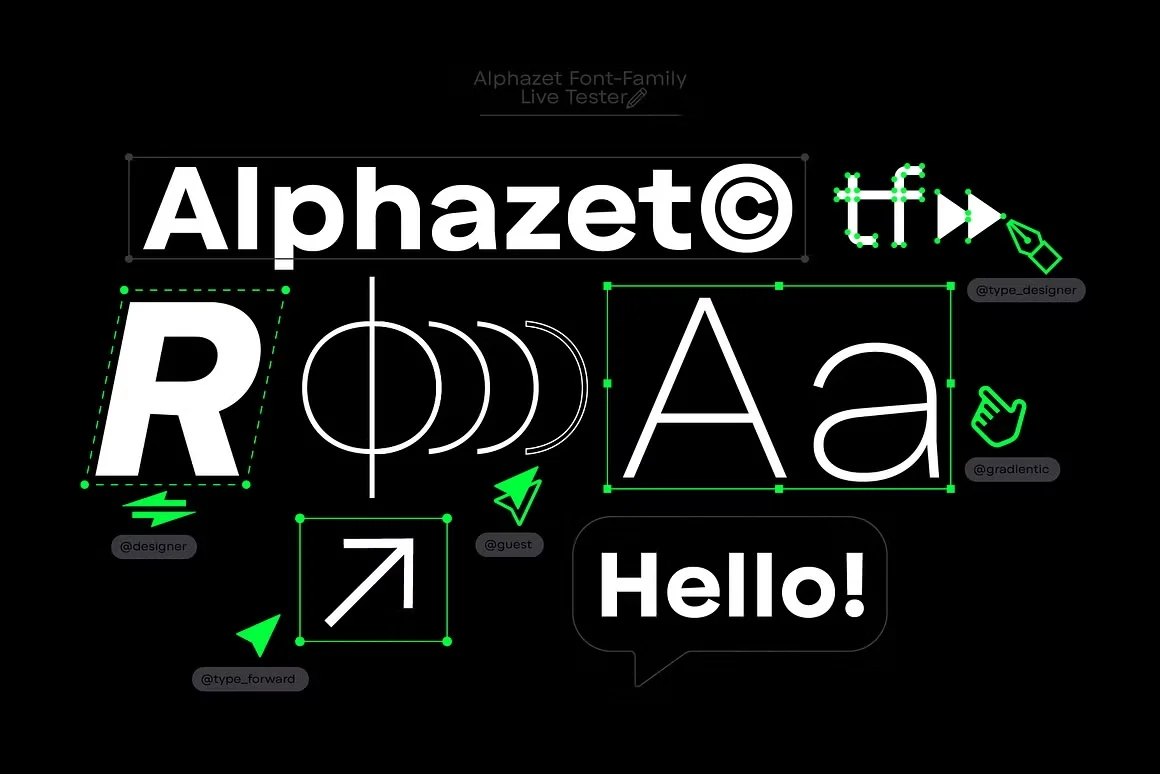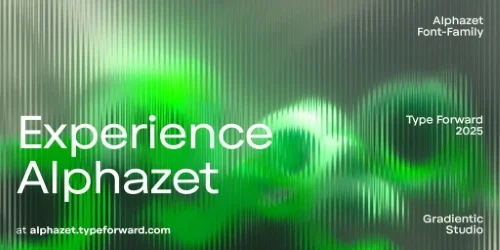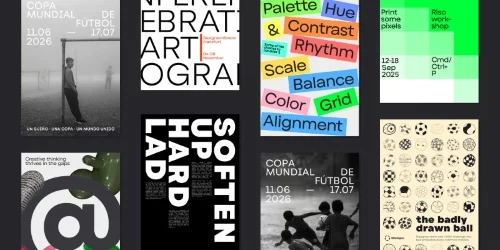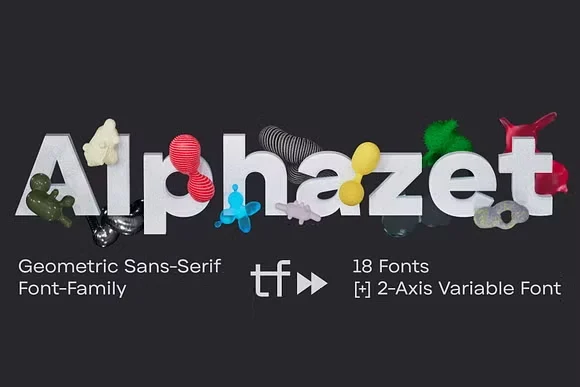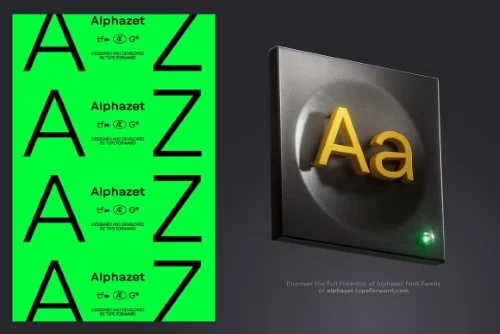
فونت هندسی مدرن Alphazet Variable Font Family
ساختار هندسی بینقص، ۱۸ استایل استاتیک + فونت وریبل ۲ محوره برای برندینگ و وب
استفاده از فونت هندسی Alphazet که با همکاری طراح برجسته Luboslav Boyanov توسعه یافته، حسی از استحکام، قدرت و مدرنیته به دیزاینهای شما میبخشد. این تایپفیس بر پایه اشکال خالص هندسی طراحی شده و با داشتن کنتراست کم در خطوط و x-height بلند، بالاترین میزان خوانایی را در متون طولانی و جذابیت فوقالعادهای در تیترها و پوسترهای بزرگ ایجاد میکند.
این مجموعه شامل ۱۸ استایل استاتیک مجزا (۹ وزن کامل از Thin تا Black به همراه نسخههای Oblique) و همچنین یک فایل کامل وریبل فونت (Variable Font) با ۲ محور تنظیم است که کنترل ۱۰۰٪ وزن و زاویه فونت را در پروژه به شما میدهد.
Ligatures, Stylistic Sets, Fractions
بیش از ۲۲۰ زبان (لاتین، سیریلیک و یونانی)
ویژگیهای شاهکار فونت هندسی Alphazet
تکنولوژی هوشمند وریبل فونت (2 Axes Variable Font)
وجود فایل وریبل فونت دو محوره به طراحان و توسعهدهندگان وب اجازه میدهد وزن (Weight) و زاویه (Slant) فونت را بهصورت دقیق و بدون محدودیت تغییر دهند و با کمترین حجم فایل بیشترین تنوع را داشته باشند.
۱۸ استایل استاتیک کامل و هماهنگ
شامل ۹ وزن مختلف از Thin، Light، Regular تا Bold و Black به همراه تمام استایلهای مورب (Oblique) برای هماهنگی کامل در تمام پروژههای گرافیکی.
معماری هندسی با خوانایی بالا (High x-Height)
ارتفاع بلند x-height در کنار تناسبات پهنتر کاراکترها باعث شده این فونت در ابعاد بسیار کوچک بدنه متون وب و چاپ و همچنین در تیترهای سنگین تبلیغاتی بینقص عمل کند.
پشتیبانی از قابلیتهای حرفهای OpenType
دارای مجموعه کامل ویژگیهای OpenType از جمله ترکیبات حروف (Ligatures)، استایلهای جایگزین (Stylistic Sets)، اعداد جدولی (Tabular Figures)، کسورات و فرمهای حساس به حروف بزرگ و کوچک.
قابلیتهای OpenType موجود در فونت هندسی Alphazet (18 Styles + 2 Axes Variable Font Family) شامل چه مواردی است؟
فونت هندسی Alphazet (18 Styles + 2 Axes Variable Font Family) شامل مجموعه کاملی از ویژگیهای OpenType مانند ترکیبات حروف (Ligatures)، مجموعه استایلهای جایگزین (Stylistic Sets)، اعداد جدولی (Tabular Figures)، کسورات و کاراکترهای حساس به حروف بزرگ است.